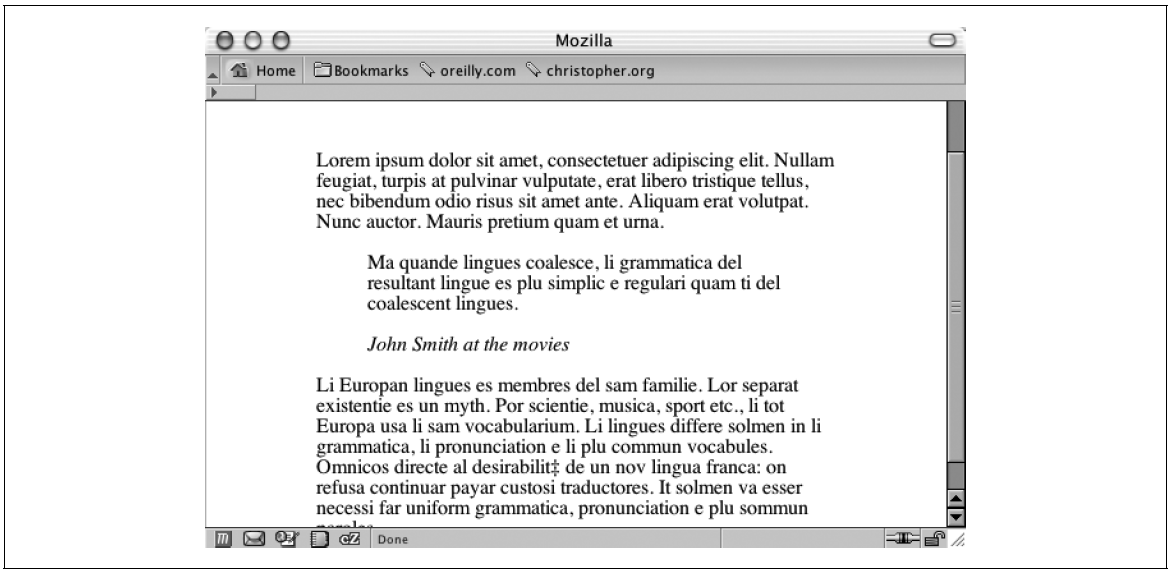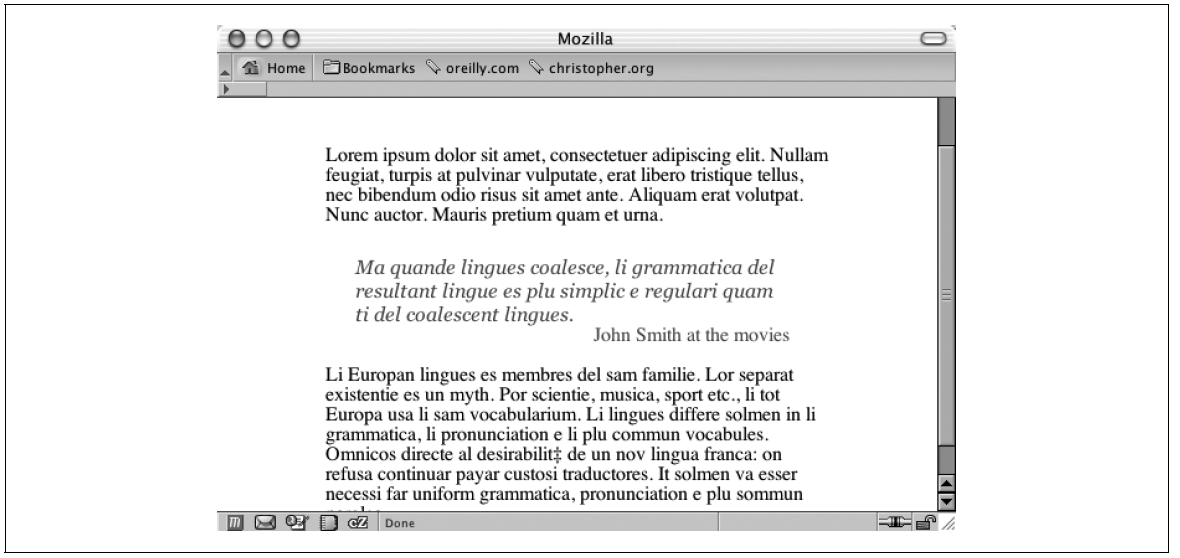
Gestaltung einer Pull Quote mit HTML-Text
Problem
Sie wollen den Text für eine "Pull Quote" (wörtlich "Lockzitat") mit Stildefinitionen versehen, damit er sich von der Standardeinstellung unterscheidet. Nicht weiter hervorgehobenen Zitaten sieht man nicht ohne Weiteres an, dass sie von einem anderen Autor stammen (siehe die nächste Abbildung), während entsprechend hervorgehobene Zitate leicht zu erkennen sind (siehe die darauf folgende Abbildung).
Abbildung: Standarddarstellung des Textes in einer Pull Quote.
Abbildung: Die Pull Quote mit eigenen Stildefinitionen.
Lösung
Verwenden Sie das Element blockquote, um eine "Pull Quote" in der Dokumentstruktur als Zitat zu kennzeichnen:
<blockquote>
<p>Ma quande lingues coalesce, li grammatica del resultant lingue es plu simplic e regulari quam ti del coalescent lingues.</p>
<div class="source">John Smith at the movies</div>
</blockquote>
Weisen Sie dem blockquote-Element nun mit Hilfe von CSS Werte für die Innen- und Außenabstände und die Farbe zu:
Danach definieren Sie die Stile für die im blockquote-Element enthaltenen p- und div-Elemente:
blockquote p {
font: italic 1em Georgia, Times, "Times New Roman", serif;
font-size: 1em;
margin: 1.5em 2em 0 1.5em;
padding: 0;
}
blockquote .source {
text-align: right;
font-style: normal;
margin-right: 2em;
}
Diskussion
Pull Quotes werden benutzt, um die Aufmerksamkeit des Lesers zu erregen, damit er Ihren Text auch weiterliest. Eine einfache Methode, Pull Quotes zu erstellen, besteht darin, die Textfarbe zu ändern. Sie können den Kontrast zum übrigen Text noch weiter erhöhen – zum Beispiel durch einen Wechsel der allgemeinen Schriftfamilie. Wird der übrige Text eines Dokuments beispielsweise in einer serifenlosen Schrift dargestellt, so benutzen Sie für die Pull Quote eine Schrift mit Serifen.